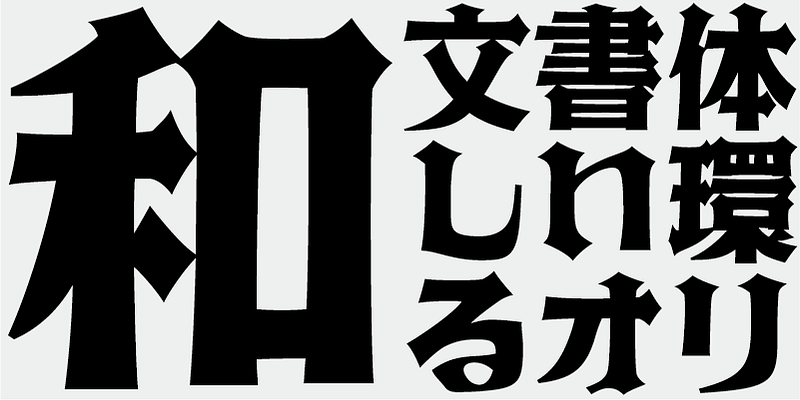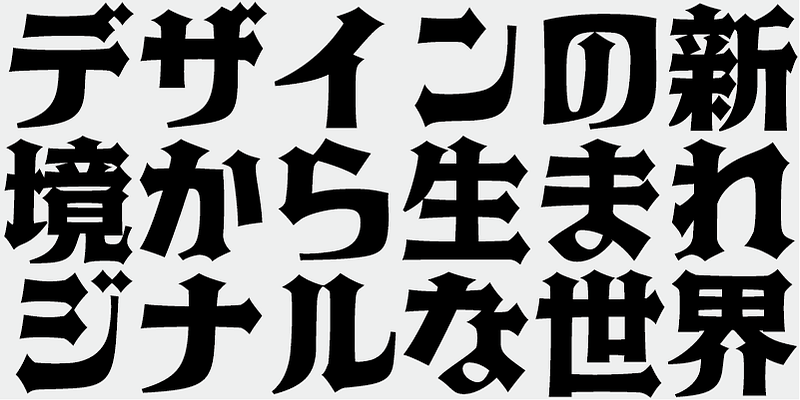
Ispirato allo stile Textura e Quadrata Gothic della scrittura occidentale, questo carattere tipografico è caratterizzato da lettere condensate del 20-30% e conferisce ai documenti un’atmosfera medievale.
Questo font include i primi 1.000 caratteri kanji scelti dalle tabelle di frequenza dei caratteri realizzate da società di giornali, case editrici e istituti di ricerca linguistica, oltre a 206 caratteri kana e segni di punteggiatura.
Nella produzione odierna di font giapponesi, i 7.000 caratteri nello standard JIS sono considerati essenziali. Ma tutti i font hanno davvero bisogno di 7.000 caratteri? Nell’era della fotocomposizione, erano necessari molti meno caratteri. FONT1000, un gruppo di progettisti di caratteri indipendenti, ha iniziato con questa semplice domanda. Abbiamo selezionato il minimo di 1.000 caratteri kanji (ideografici) necessari per la composizione in giapponese e abbiamo creato attivamente caratteri tipografici e font per supportarlo. Questo set di 1.000 caratteri kanji è stato selezionato utilizzando dati sulla frequenza dei caratteri compilati da società di giornali, case editrici e organizzazioni di ricerca linguistica, e così via e include anche caratteri sillabici kana e segni di punteggiatura. FONT1000 è stata costituita nel 2001 con 25 progettisti e 25 caratteri tipografici. Oggi abbiamo 130 caratteri tipografici e siamo cresciuti fino a includere circa 40 membri, rendendo possibile lavorare su font con più caratteri.